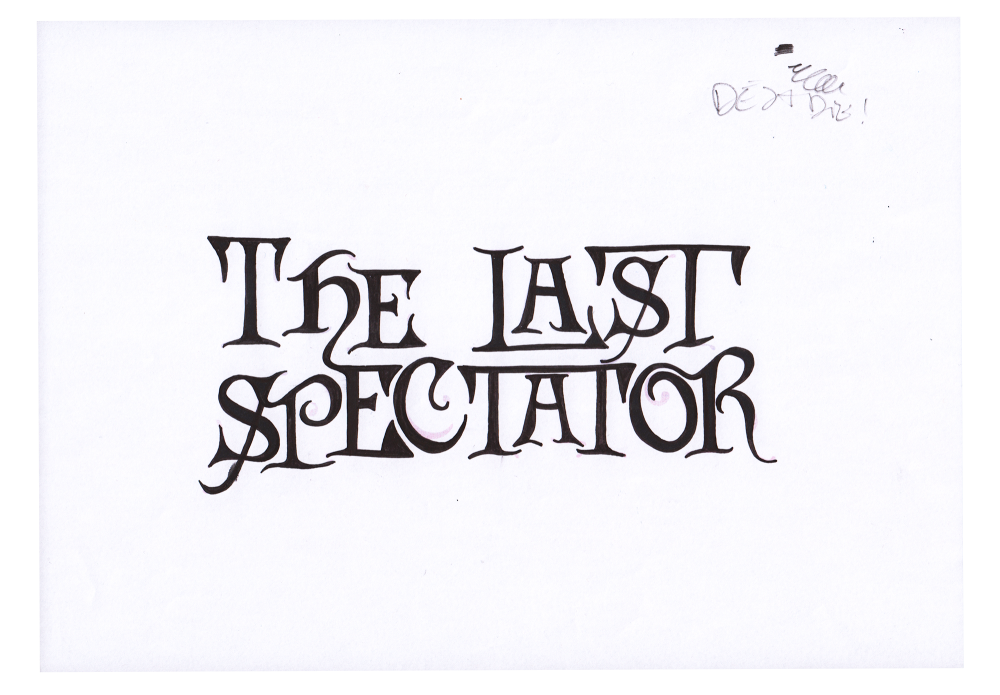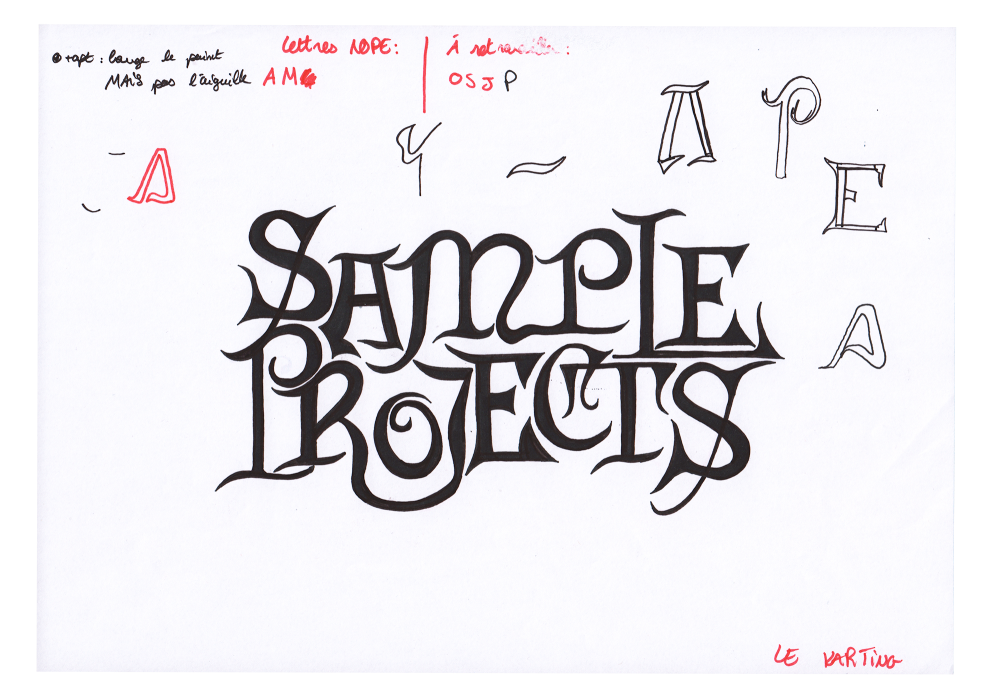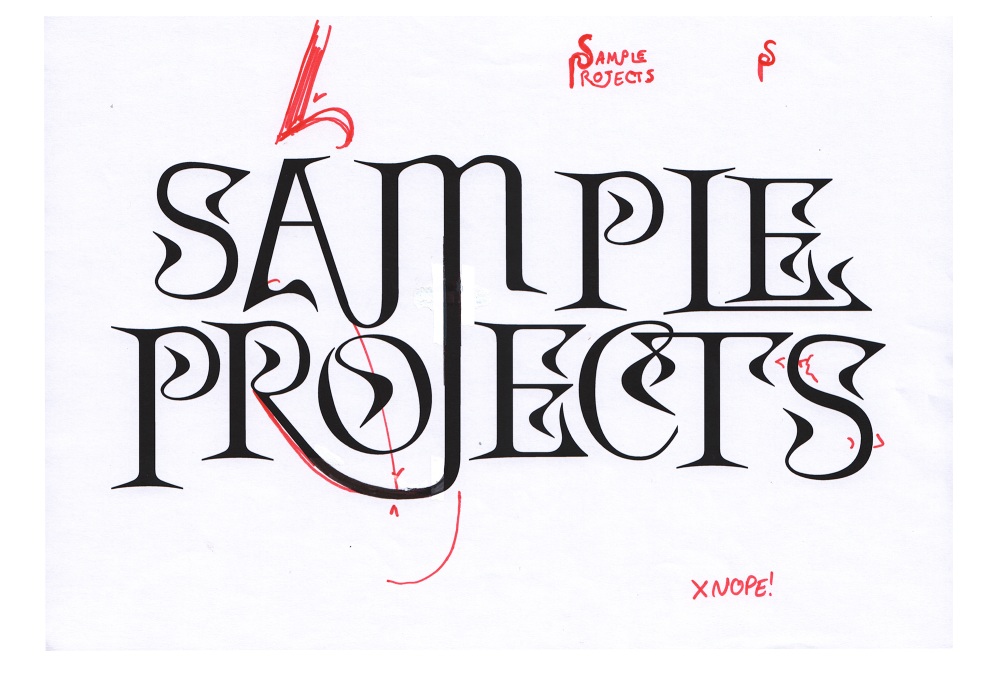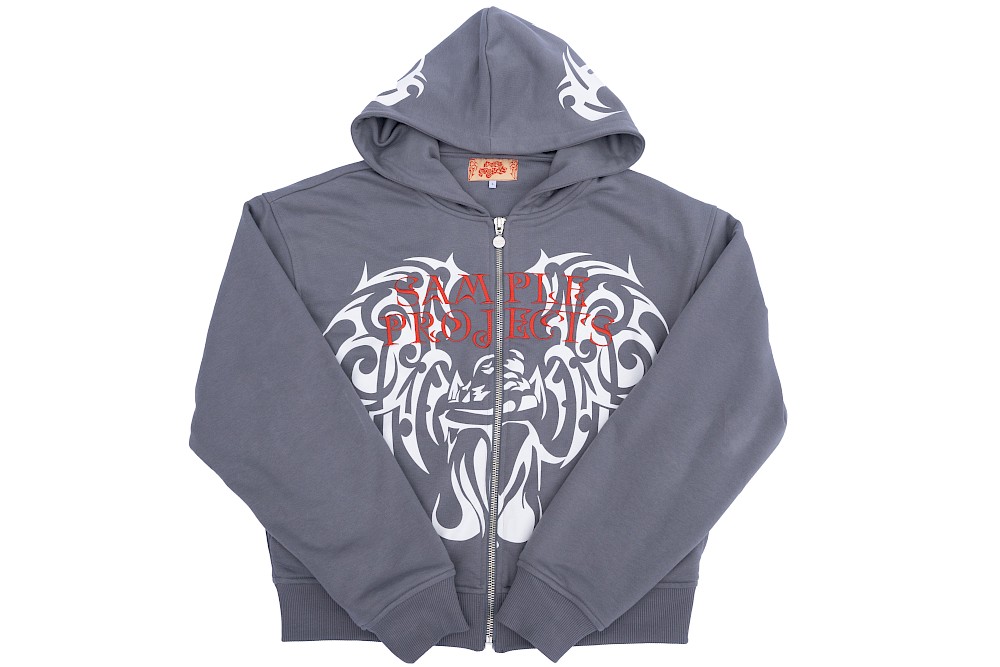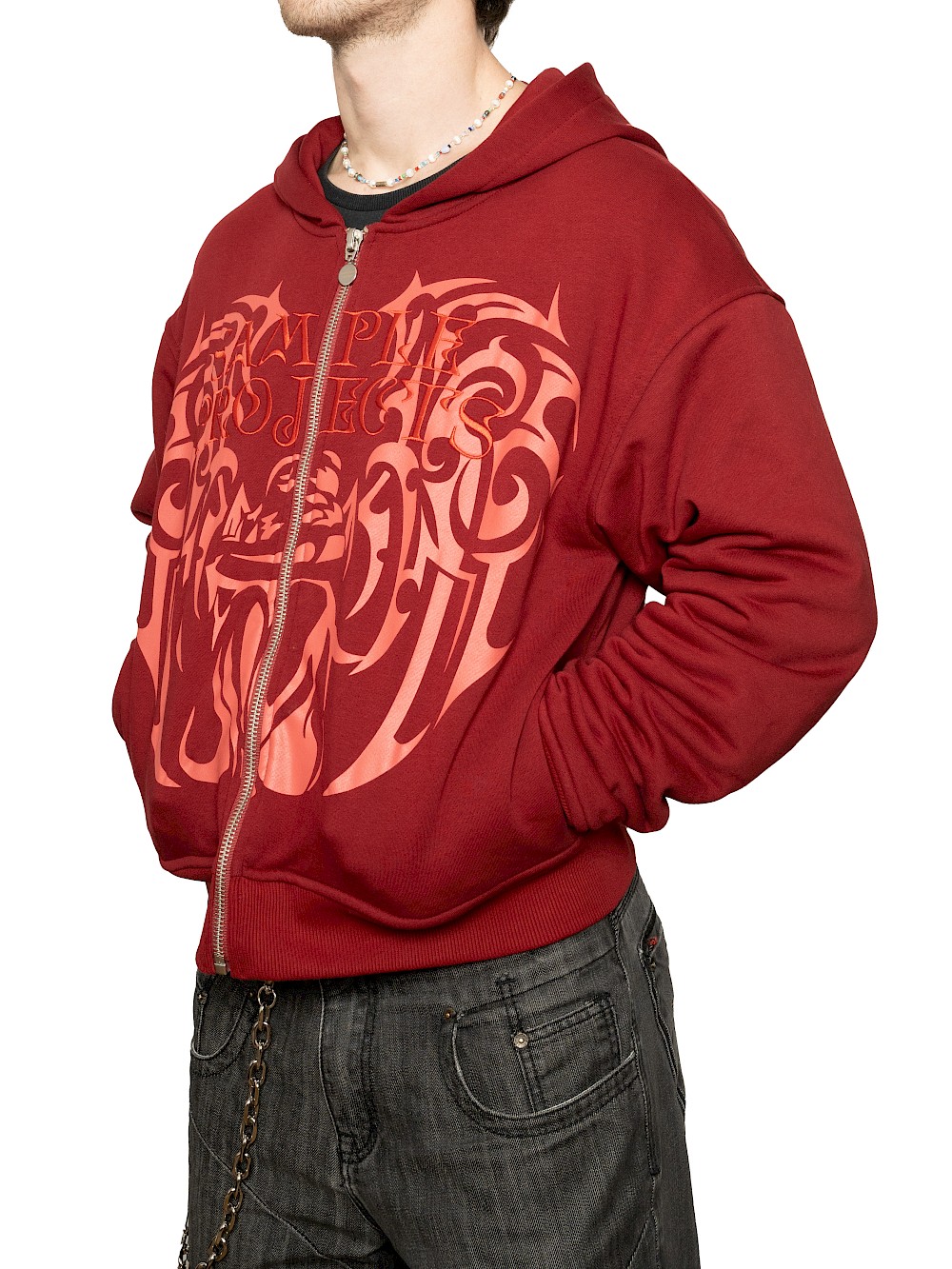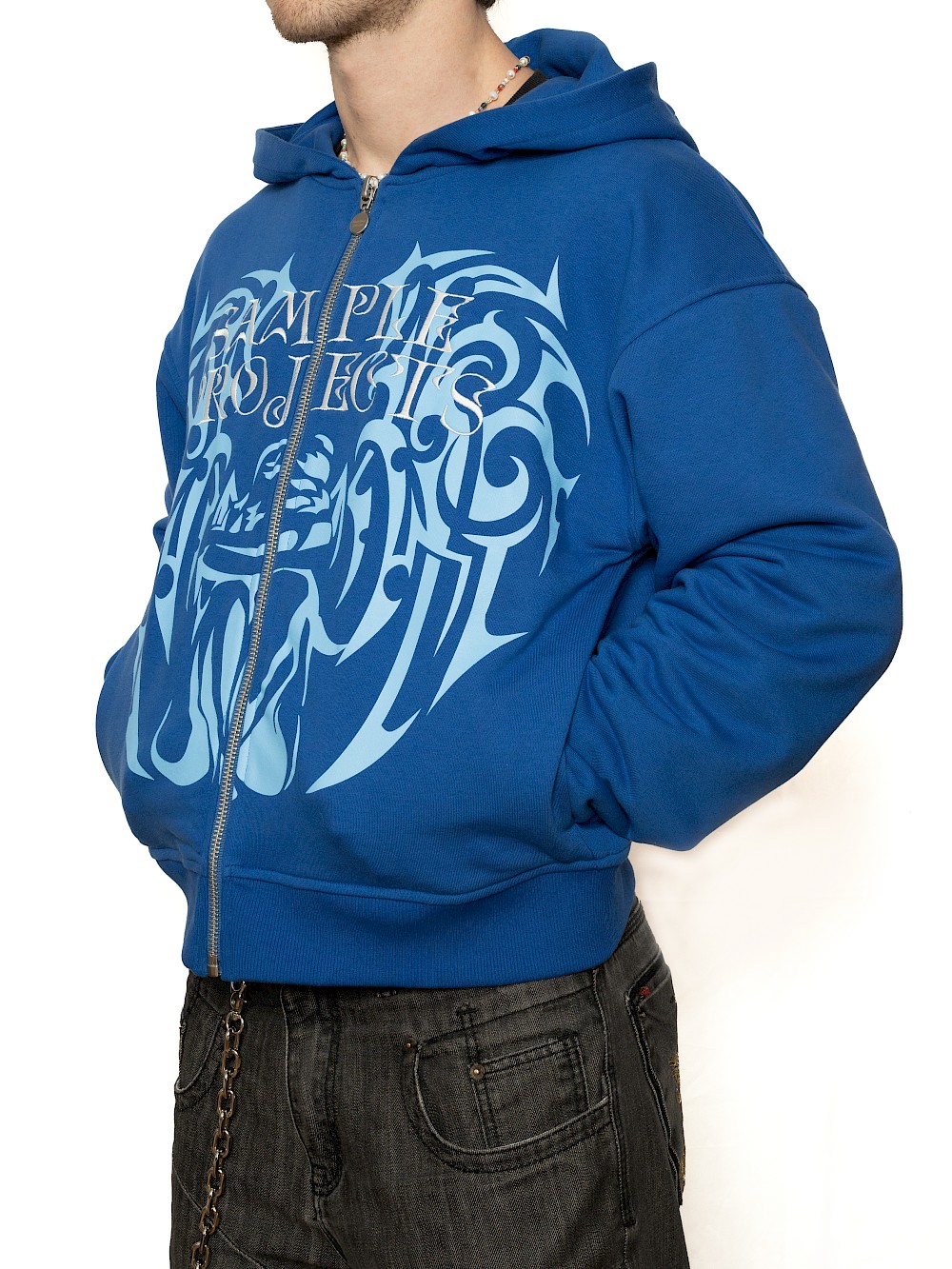
Pour la création de cette typo, j'avais commencé par faire une fresque de références afin de choisir une typo qui allait m'aider à driver mon dessin. J'ai décidé de prendre la "Cardinal", dispo sur dafont. Je trouvais que son dessin respectait à la fois le côté diabolique et elfique. À la suite de ça, j'ai décalqué et redessiné en fonction du dessin que je voulais pour mon custom final.
Des années encore je reste très content du résultat! C'était un maxi accomplissement d'avoir un lettrage brodé sur un pull mouhahaha
Entre la seconde et la troisième année de DNMADe, on nous demande de faire un stage. En tant que master galère, je m'y prends en retard et je mets beaucoup de temps à trouver quelque chose. Je finis en plein été par trouver un mec de mon âge, qui a une marque de vêtements et qui cherche un pélo pour faire un lettrage pour une collection d'hoodies qui sortira à la rentrée. Les seuls mots-clefs de la collection seront: diabolique & elfique 𓆩ꨄ︎𓆪࿔‧ ֶָ֢˚˖𐦍˖˚ֶָ֢ ‧࿔𓆩ꨄ︎𓆪
SPectator